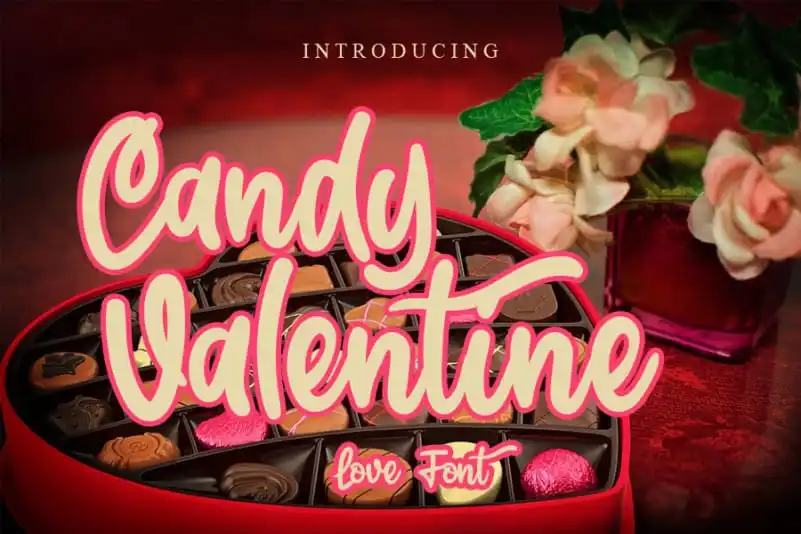
Candy Valentine Display Font – Download Grátis
A Candy Valentine Display Font é uma fonte escrita a mão com um toque adoravelmente fofo, cuidadosamente formada para se tornar verdadeiramente querida. Ela mantém um charme sofisticado que remete à calligrafia, mas também transmite atualidade e frescura inegável. Esta versatilidade atrairá ideias de criatividade em uma variedade de aplicações, desde os famosos cabeçalhos até os textos mais sutis, passando por rótulos para ferramentas. Ideal tanto para aqueles que buscam um toque delicado e encantador quanto para designers que desejam adicionar um pouco de personalidade à sua tipografia, esta fonte escrita a mão é perfeita para criar uma atmosfera de conforto e elegância em qualquer projeto visual.